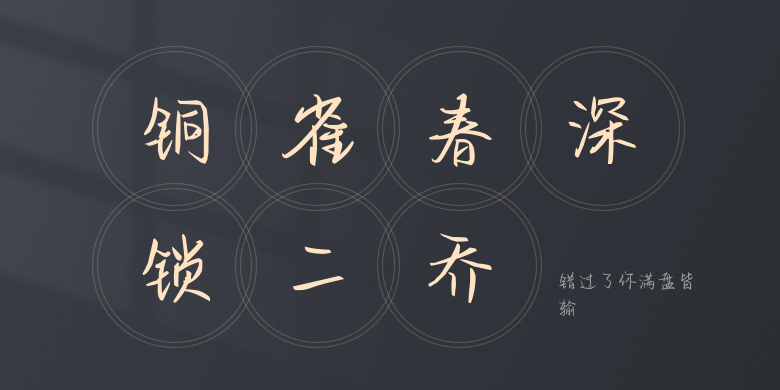
错过了你满盘皆输
错过了你满盘皆输,这款字体结构工整、笔画清晰,兼顾美观与易读性,适用于标题、正文、海报、包装、LOGO 等多种场景。字形优雅稳定,风格百搭耐看,适配日常排版与创意设计,让文字呈现更舒适、更具质感。错过了你满盘皆输一笔一画,皆是细节,以均衡的比例、流畅的线条打造舒适视觉体验,字形端正大气,风格简约现代。无论是商业设计、品牌宣传还是日常排版,都能轻松驾驭,让文字更有格调与力量。错过了你满盘皆输字体下载。